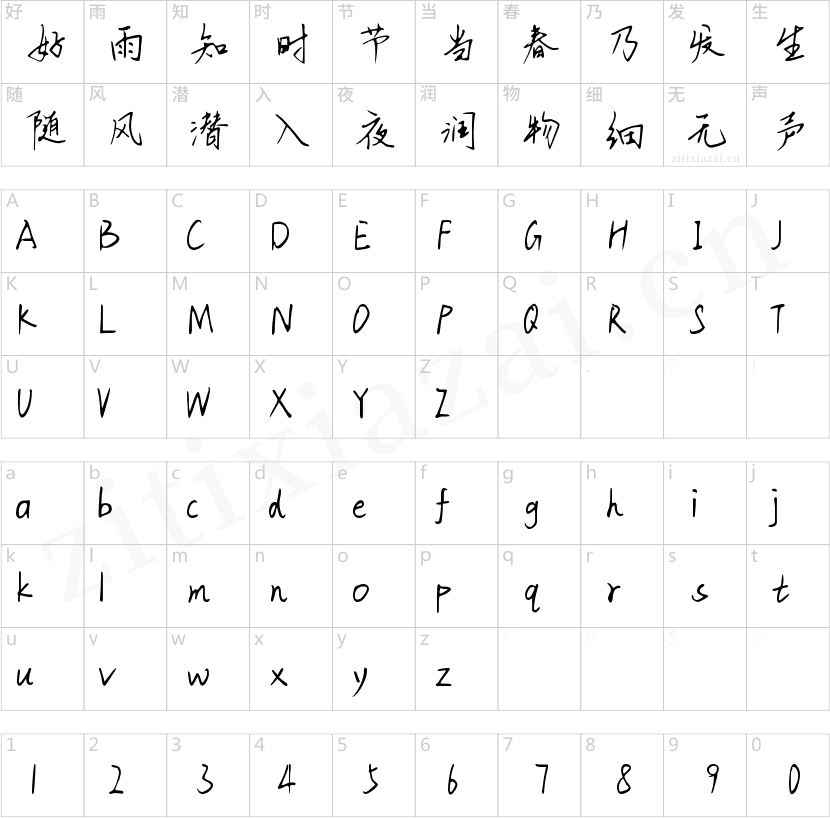
Aa时光不负有心人
Aa时光不负有心人,这款字体结构工整、笔画清晰,兼顾美观与易读性,适用于标题、正文、海报、包装、LOGO 等多种场景。字形优雅稳定,风格百搭耐看,适配日常排版与创意设计,让文字呈现更舒适、更具质感。Aa时光不负有心人一笔一画,皆是细节,以均衡的比例、流畅的线条打造舒适视觉体验,字形端正大气,风格简约现代。无论是商业设计、品牌宣传还是日常排版,都能轻松驾驭,让文字更有格调与力量。Aa时光不负有心人字体下载。
Aa时光不负有心人字体
Aa时光不负有心人是一款非常具有艺术性的字体,它的设计灵感来源于对古典艺术的研究,同时又融入了现代字体设计的元素。字形优美,笔画粗细变化自然,给人以大气、典雅的感觉。Aa时光不负有心人是一款既传统又现代的字体,它的设计充满艺术感,美观大方,实用性也非常强。无论是对于设计师还是对于普通读者来说,都是一种非常不错的字体选择。Aa时光不负有心人适合用于具有艺术感的场合,比如海报、宣传单张、书籍封面等。由于其字形流畅且具有动态感,也适合用于大量的文本排版,如报纸、杂志等。
Aa时光不负有心人